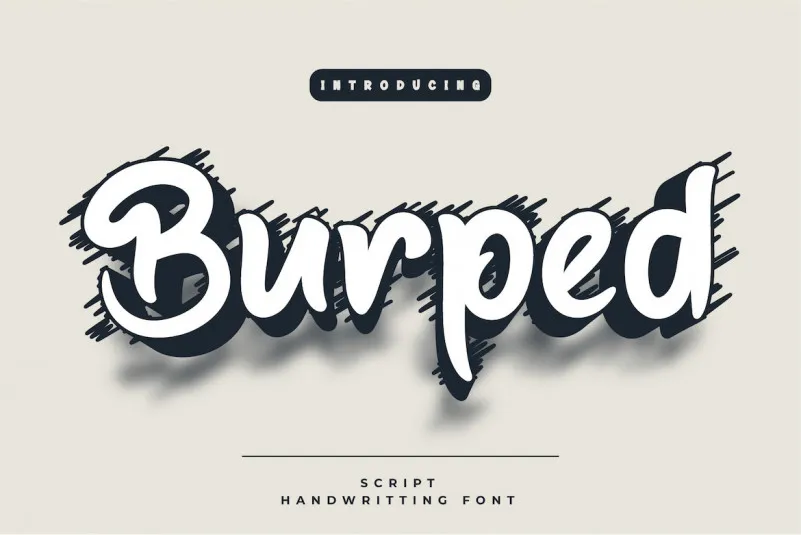
A Burped Font é uma tipografia desenhada com delicadeza e elegância, parecendo perfeita para projetos especiais onde a simplicidade do texto e a beleza das cabeçetas podem fazer um impacto imediato. Suas linhas leves mas belamente arredondadas se destacam em design de páginas web, infográficos ou qualquer outro tipo de projeto gráfico que requer um toque especial e delicado. Seja para criar uma identidade visual única, destaque seu texto com elegância ou mesmo apenas manter os títulos atraentes, essa fonte é ideal. Productype criou algo mais do que simplesmente outra font; ela traz beleza à forma de cada letra. Engane-se e não acredite na aparência delicada dela se você só usar para títulos menores ou subtítulos; ela ganha sua força nas páginas inteiras quando usada no seu verdadeiro alcance. Seja qual for o projeto, Burped Font é um escolher certa.